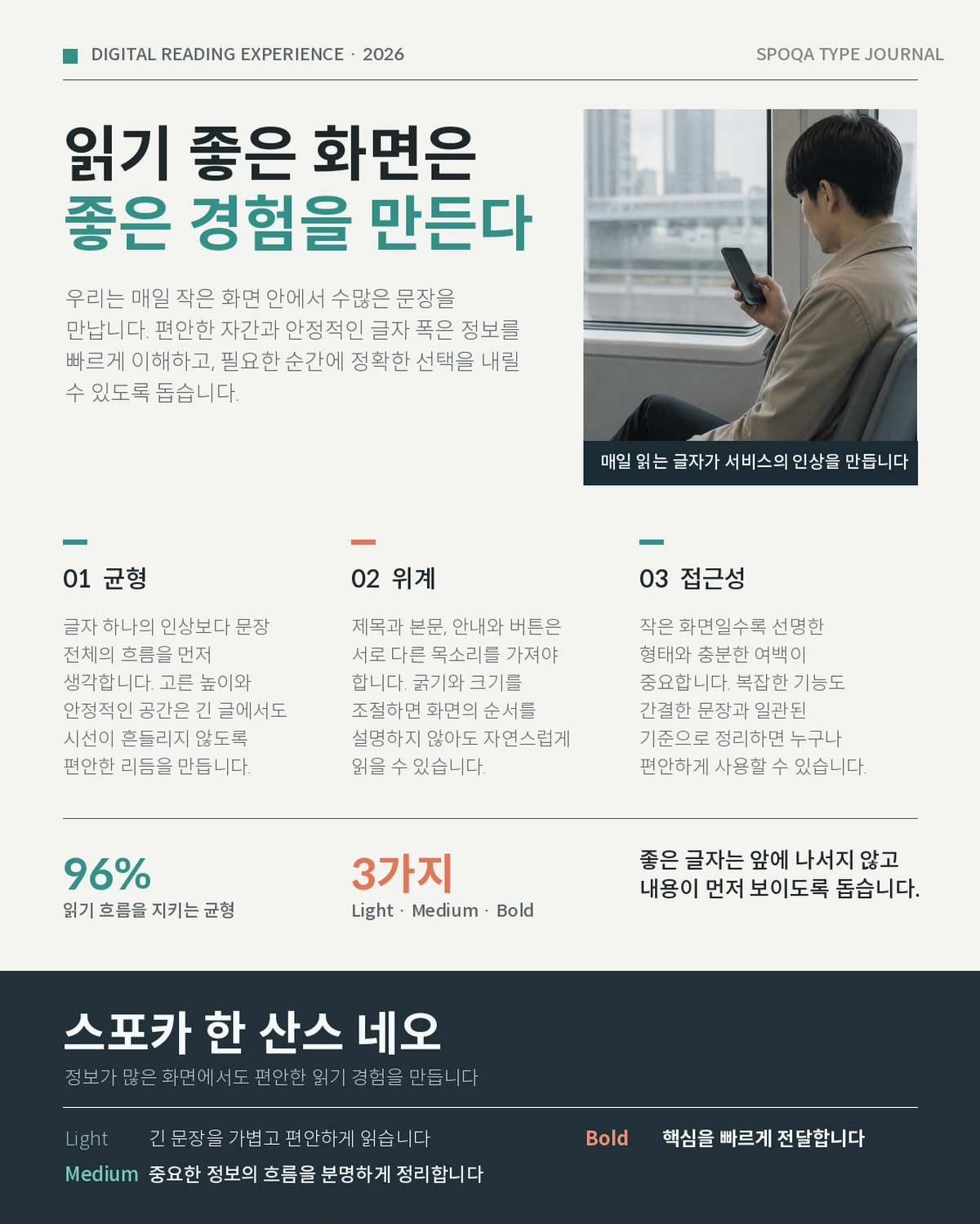
스포카 한 산스 — 스포카에서 배포하는 무료 폰트입니다. 본고딕을 다듬어 한국어와 일본어, 영문이 한 화면에서 고르게 어울리도록 만든 본문용 고딕체
결제 서비스 도도 포인트를 운영하던 스포카가 2015년 한글날에 공개한 서체입니다. 만든 이유가 실무적입니다. 여러 글꼴을 섞어 쓰다 보니 브랜드에 일관성이 없었고, 일본으로 서비스를 넓히면서 한국어와 일본어, 영문, 숫자가 함께 어울리는 전용 글꼴이 필요해졌습니다.
바탕으로 삼은 것은 오픈 폰트 라이선스로 풀린 본고딕입니다. 다만 그대로 쓰지 않은 이유가 두 가지 있었습니다. 하나는 숫자 형태가 아쉬웠던 것이고 다른 하나는 파일이 너무 컸던 것입니다. 멤버십 서비스라 숫자를 쓸 일이 유난히 많았기 때문입니다. 그래서 숫자는 오픈소스 서체 라토를 가져오되 라토 특유의 둥근 획 끝을 깎아 한글과 톤을 맞췄고, 16MB에 이르던 용량은 서브셋으로 441KB 수준까지 줄였습니다.
굵기는 Thin부터 Bold까지 다섯 가지이고 한국어판과 일본어판이 따로 있습니다. 제작사는 용량을 줄인 서브셋 판도 함께 내놓는데, 폰트픽이 서비스하는 파일은 현대 한글 11,172자를 모두 담은 쪽이라 어떤 글자를 넣어도 빠지지 않습니다. 오픈 폰트 라이선스로 수정과 재배포가 자유롭습니다.